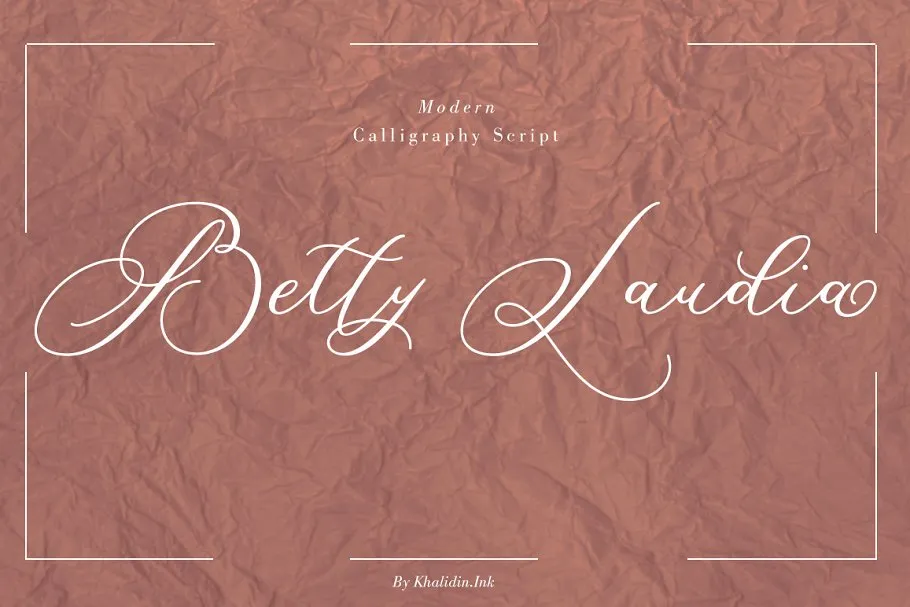
Betty Laudia Script Font – Download Grátis
Betty Laudia Script é uma nova abordagem moderna para os tipos de letra script. De Khalidin.Ink, essa fonte apresenta um estilo simples e elegante, perfeita para adicionar sofisticação e modernidade a qualquer projeto gráfico. Com suas linhas irregulares e caracteres dançantes, Betty Laudia oferece um toque feminino e luxuoso sem perder aquela elegância moderna que tanto apreciamos no mundo da tipografia. Ideal para trabalhos delicados e sofisticados, essa fonte é perfeita para designers buscando incorporar um ar refinado às suas criações. Não apenas dá uma sensação de feminilidade, Betty Laudia também adiciona um toque moderno a qualquer projeto que ela seja usada em, tornando-a uma opção ideal tanto para designs pessoais quanto profissionais. Com seu estilo inovador e versatilidade única, Betty Laudia Script não apenas reafirma o lugar de Khalidin.Ink no mundo das fontes, mas também oferece um recurso valioso para qualquer designer interessado em incorporar nuances sofisticadas em seus projetos.